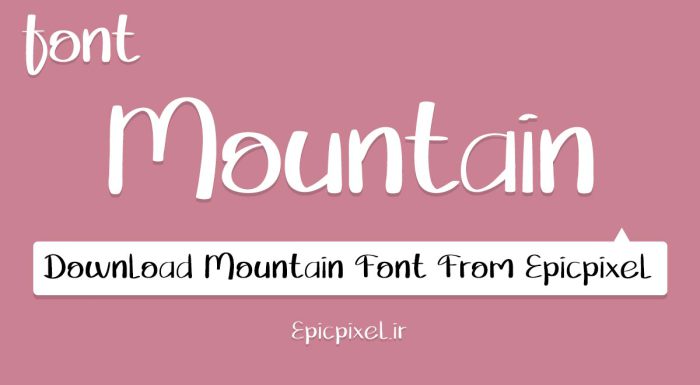
فونت Mountain انگلیسی
دانلود فونت Mountain انگلیسی Font مونتین |
| ⭐ مجموعه فونت | دانلود فونت انگلیسی کوهستان Font Mountain |
| ⭐ توضیحات | فونت کوهستانی را معرفی میکنیم، خطی روستایی و ماجراجویانه، و حروف دستنویسی که روح فضای باز را بازتاب میدهد. این فونت با حروف ناهموار و جذابیت ارگانیک خود، جوهر مناظر کوهستانی را به تصویر می کشد.
فونت کوه که برای طرحهای با مضمون فضای باز، آرمهای ماجراجویی و پروژههای الهامگرفته از طبیعت ایدهآل است، حسی از طبیعت وحشی و کاوش را اضافه میکند و متن شما را در زیبایی و شکوه کوهها غوطهور میکند. |